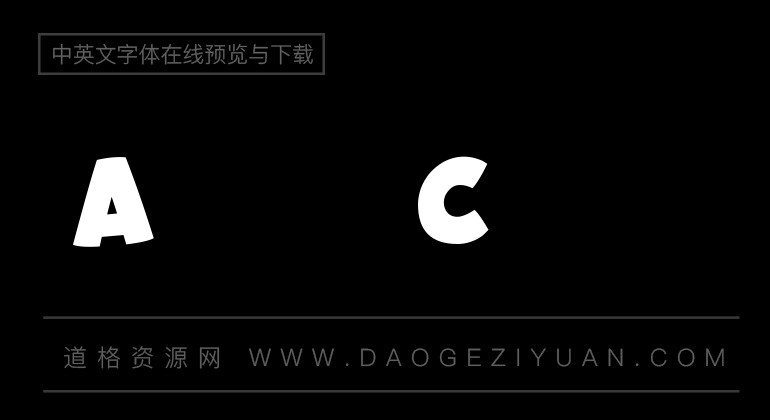
Action Comics 是一款经典的英文字体,它的特点是粗体,比较有力量感,可以用来表达强烈的情感。它的设计灵感来自于美国漫画书中的英雄形象,有着浓重的漫画风格,可以用来制作海报、logo、海报等。此外,它还有一些特殊的字体,可以增强文字的表现力,更能体现出漫画书中的英雄特色。内容介绍
Action Comics是一款非常不错的手写艺术字体,具有很好的视觉感,适合于文化类的宣传设计、商业类品牌的广告和产品包装设计以及个性化文字排版等较多场景。